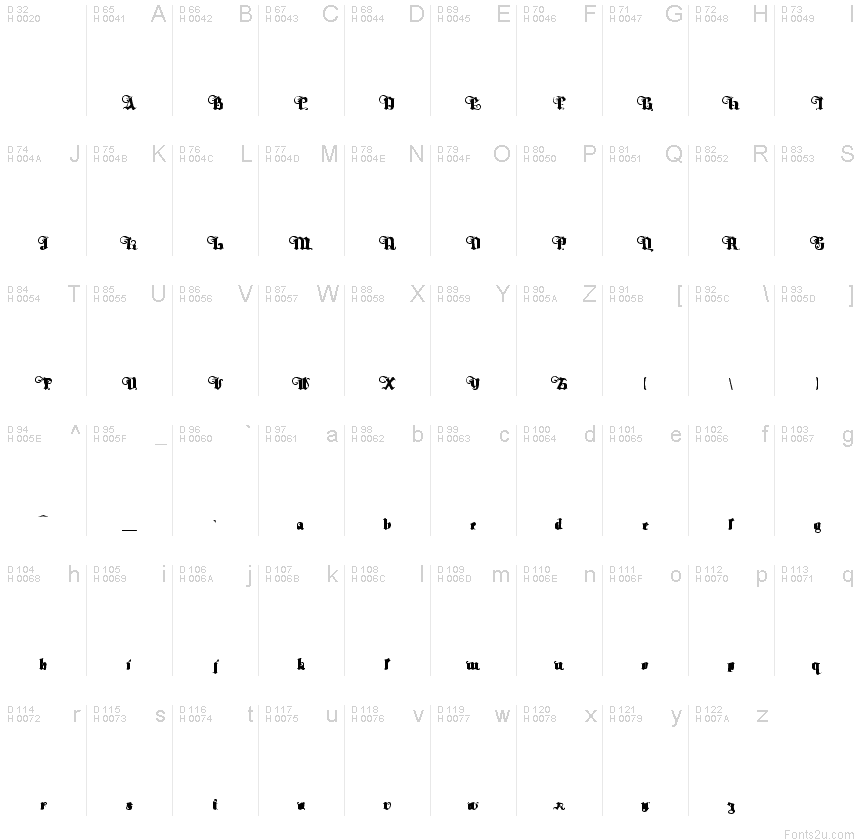
Tyrfing, stworzony przez Davida F. Nalle z Ragnarok Press, to darmowy gotycki krój pisma o silnym charakterze blackletter, wzbogacony o dramatyczne, zawijane detale. Teksturę tworzą tu wyraziste pionowe kreski, ostre łączenia i nieoczekiwane pętle, dzięki którym czcionka nie sprawia wrażenia ociężałej czy muzealnej.
Idealnie pasuje do okładek książek fantasy, logo gier, otwarć rozdziałów, plakatów eventowych i tytułów, w których chcesz uzyskać klimat dawnych czasów z odrobiną teatralnego polotu. Jako darmowy font, sprawdzi się również w monogramach lub krótkich oznaczeniach marki, ponieważ dekoracyjne zawijasy nadają nawet pojedynczym literom heraldycznego, baśniowego charakteru.